新しい箇条書きの表現
昨晩のアップルの「Apple Special Event. March 25, 2019.」イベントでは、次のような表現が見られました。
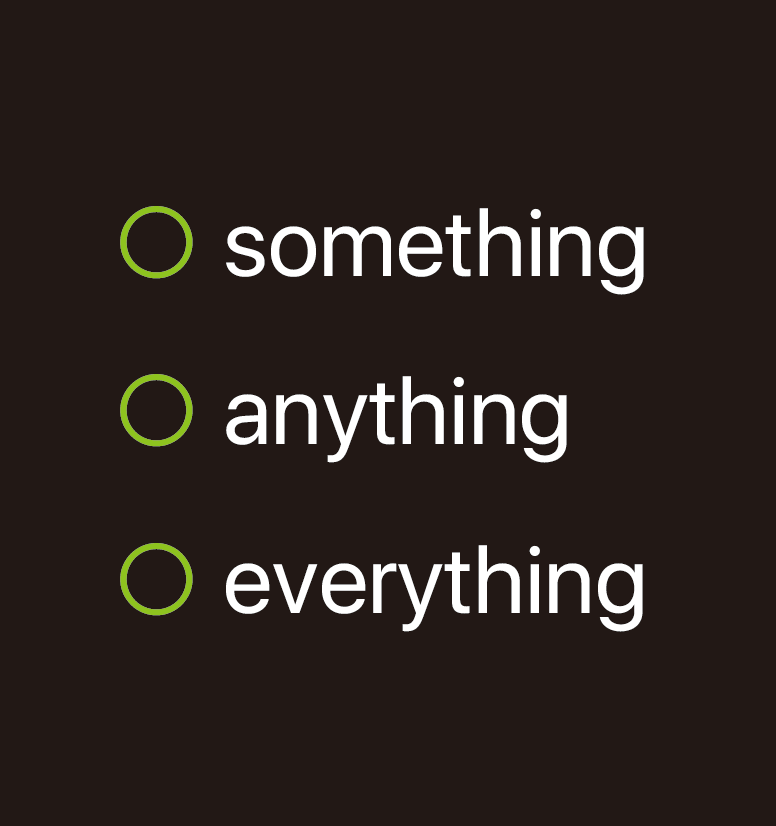
最初に箇条書きの○が提示され、次のすべての項目をクリアしたというニュアンスで✓が追加されます。
Illustratorで[字形]パネルを開き、パネル下部でフォントを「SF」(San Franciscoフォント)に指定、そして、[表示]に「欧文合字」を選択すると「○の中に✓」の文字があります。
ところが、これをダブルクリックして挿入されるのは「✓」のみ。○は入りません。「○の中にA」などは問題なく挿入されるのですが…
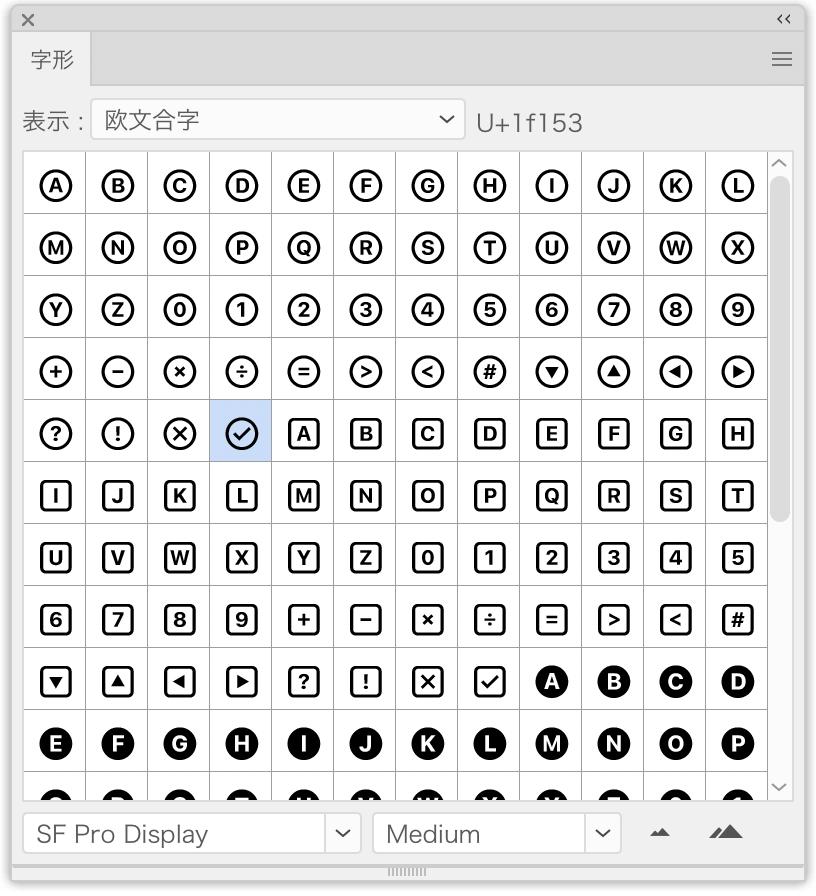
次のようにして実現できます。
✓に続いて○を挿入する(U+20dd)
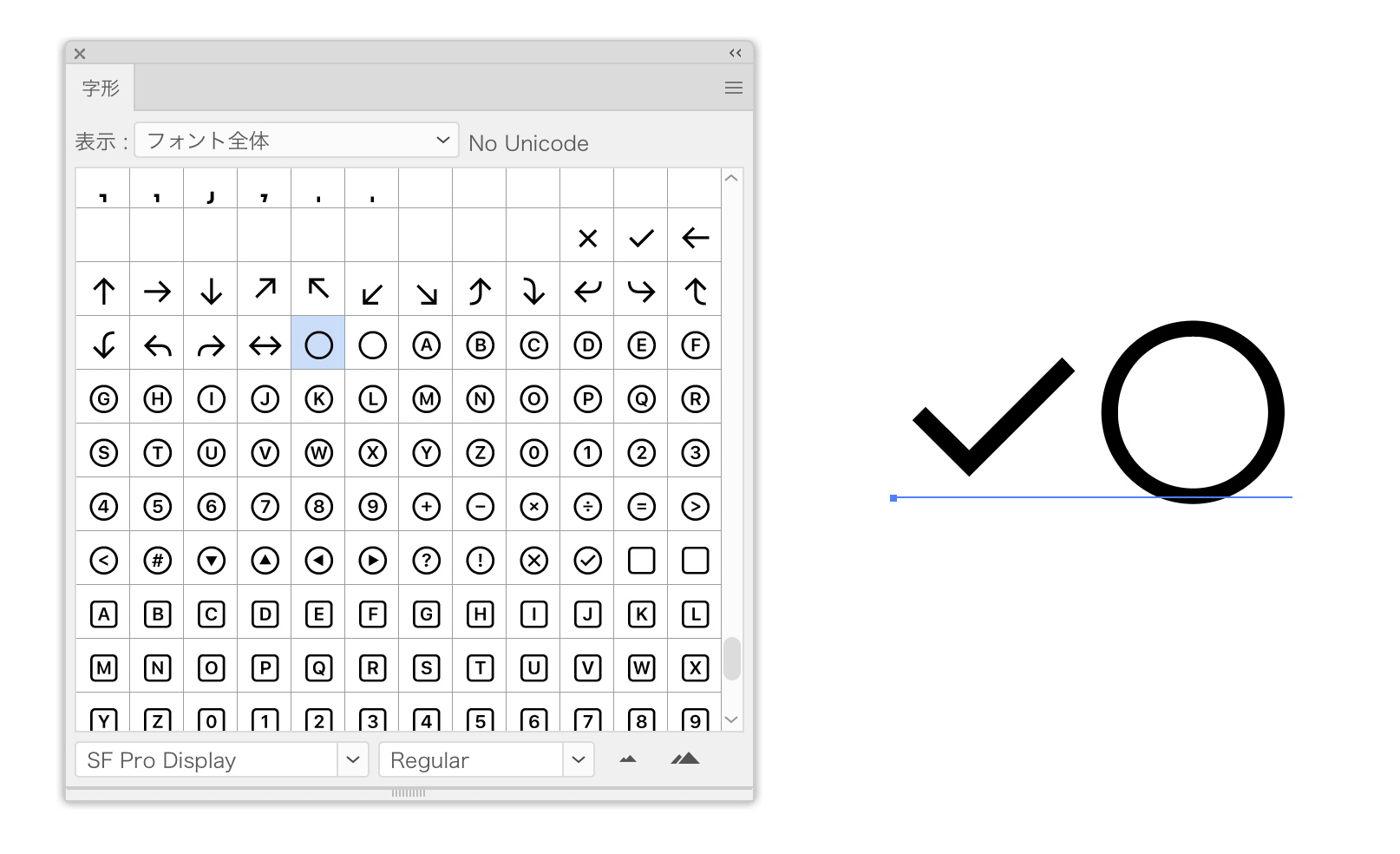
2つの文字を選択する
[OpenType]パネルで[欧文合字]オプションをオンにする
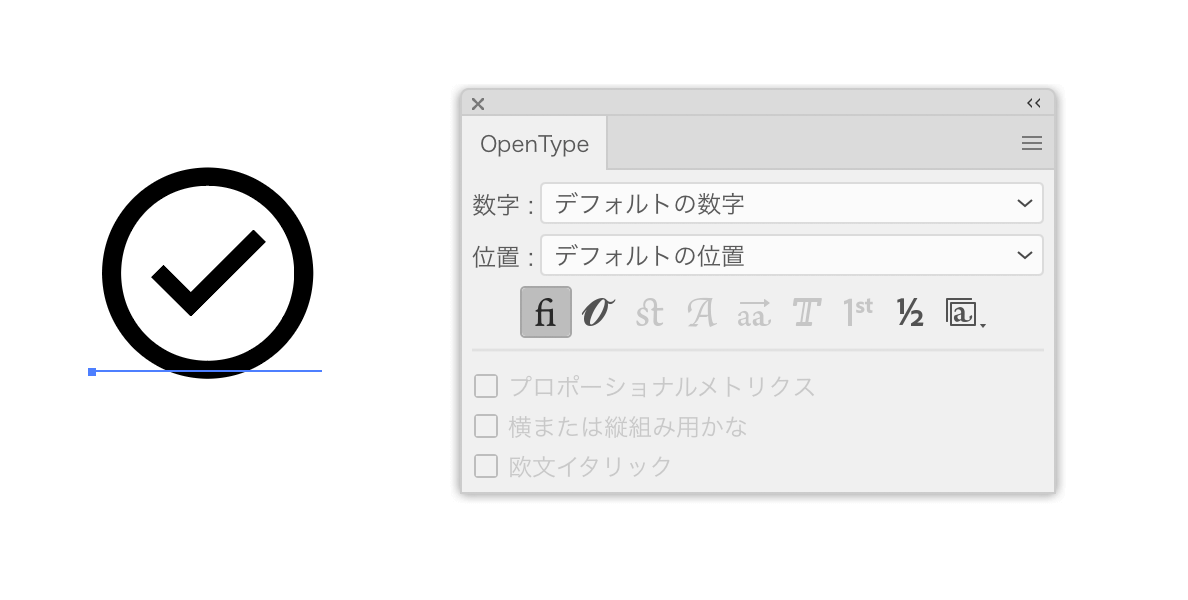
IllustratorでのSFの合字
どうやらちょっとクセがあります。
- 合字オプションがデフォルトでオンでも「○」を入れた時点でオフになってしまう
- 2つの文字を選択してからでないと、合字にできない
追記:「SF Symbols」
2019年06月、アップルから「SF Symbols」がリリースされました。
SFフォントと同じ9つのウェイト(太さ)と大中小の3つのスケール、ダークモード対応で同梱されており、開発者はiOS 13およびtvOS 13, watchOS 6以降でこのシンボルをナビゲーションやツールバー、アクションなどのシンボルとして利用することができるそうです。
また、「SF Symbols.app」というプレビュー用のアプリがリリースされています。